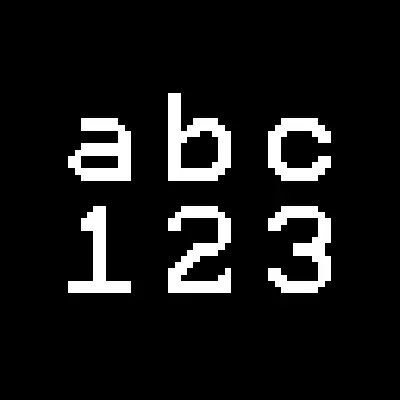
Slightly Improved Font (32x)
Slightly Improved Font (32x): что это и зачем нужно​
Slightly Improved Font 32x представляет собой ресурспак, который изменяет ванильный шрифт игры. Он делает текст более четким и читабельным за счет увеличения разрешения символов.
Ключевые возможности​
• Улучшенная версия стандартного шрифта Minecraft
• Текстуры шрифта в разрешении 32x
• Сохранение оригинального стиля игры
• Повышение комфорта чтения игрового текста
Итог​
Простой и полезный ресурспак для тех, кто хочет сделать стандартный шрифт игры более качественным и приятным для глаз.